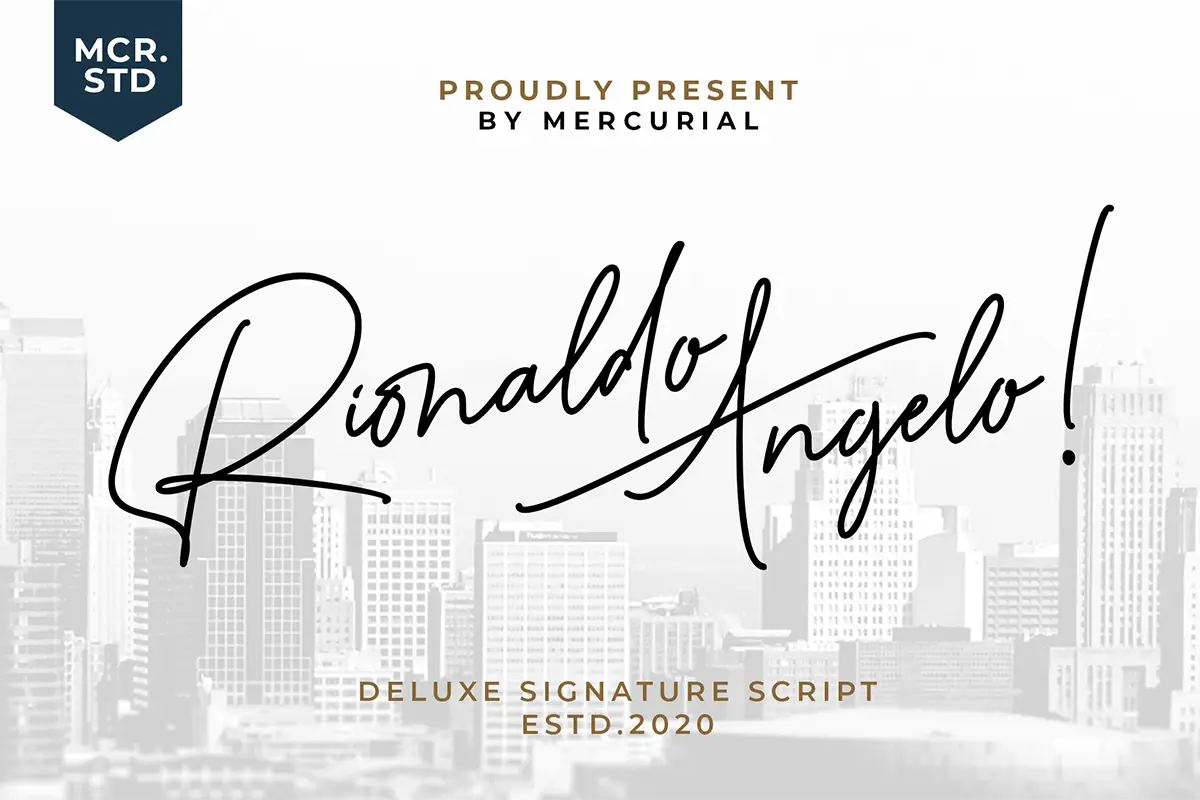
فونت سبک امضاء Rionaldo Angelo
فونت سبک امضاء Rionaldo Angelo ترکیب زیبایی از ظرافت کلاسیک و طراحی مدرن دست‌نویس است. این فونت با حفظ تأثیرات خوشنویسی سنتی، حس تازه و امروزی دارد و برای سرنامه‌ها، عناوین و طراحی لوازم‌التحریر انتخابی فوق‌العاده محسوب می‌شود.
• استایل دست‌نویس با جلوه‌ای خاص
• ترکیب ظرافت و مدرنیته
• ایده‌آل برای برندینگ، دعوت‌نامه‌ها، طراحی‌های رسمی و هنری